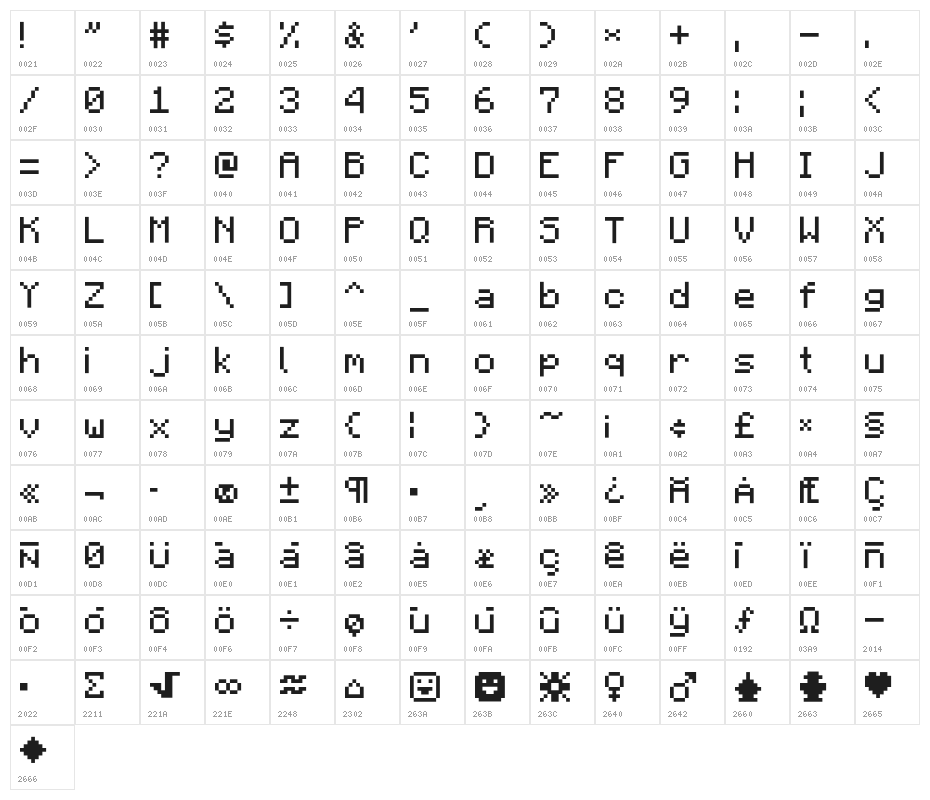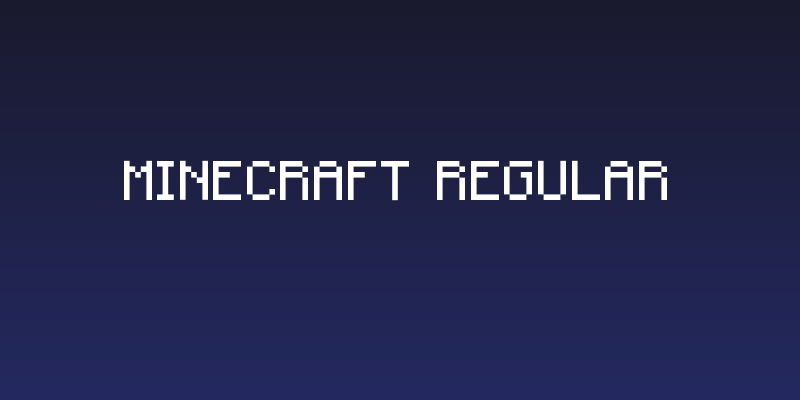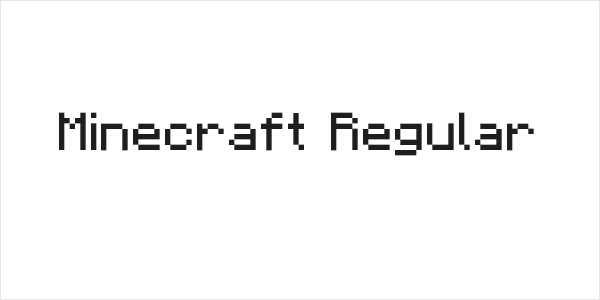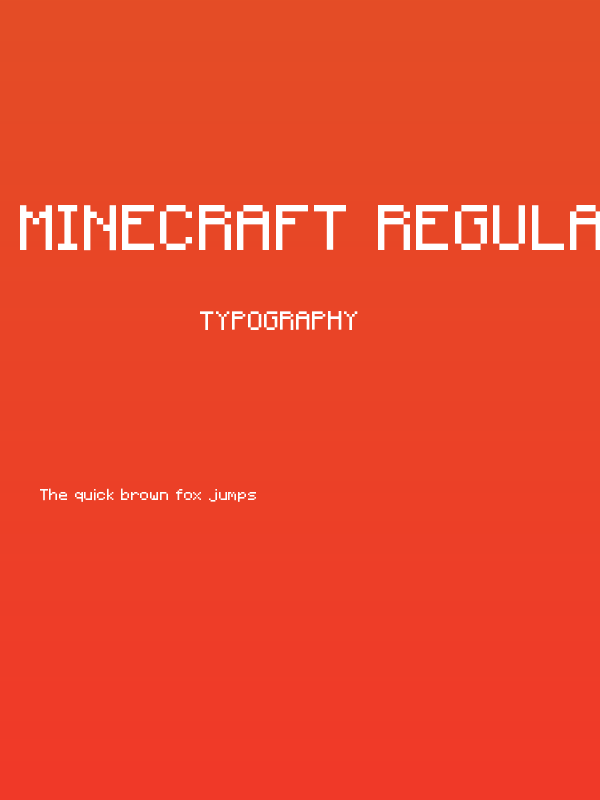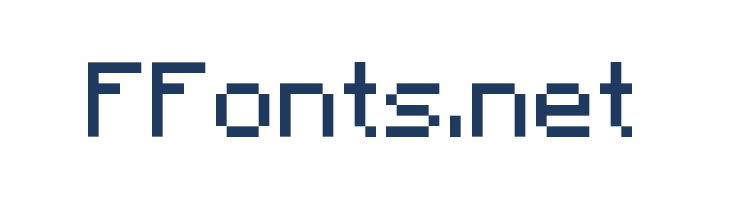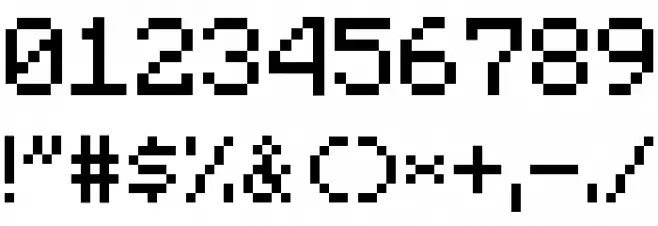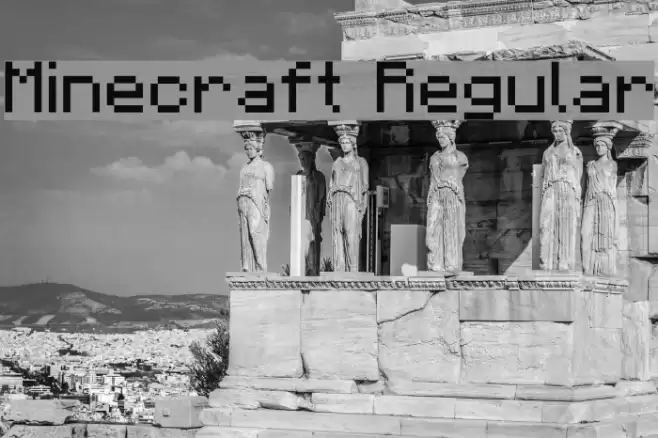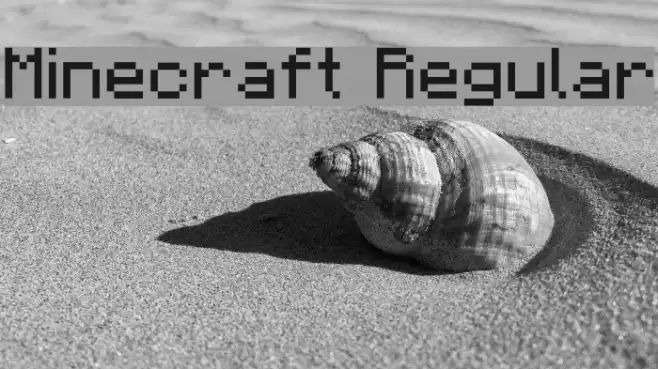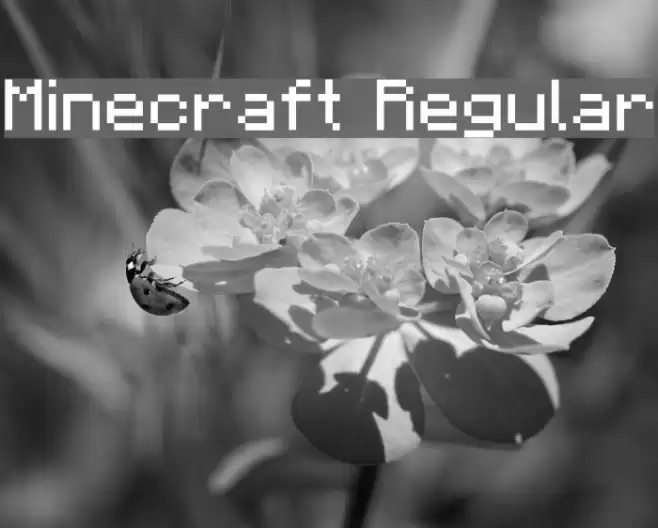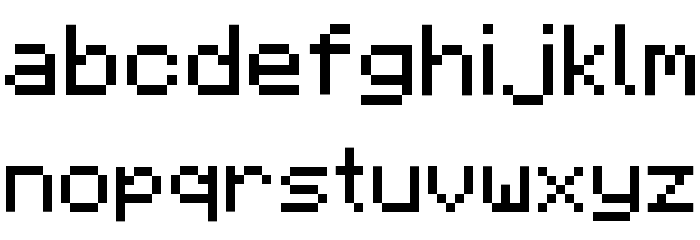
Minecraft Regular Font
✎ Pixel
| النمط العام | Retro, Digital |
| حالة الاستخدام | Headlines, Logos, Digital Art |
| مشاريع مقترحة | Ideal for video game design, retro-themed graphics, digital art projects, and any creative work that seeks a nostalgic or playful vibe. |
| المؤلف | Fonts by Måns Grebäck |